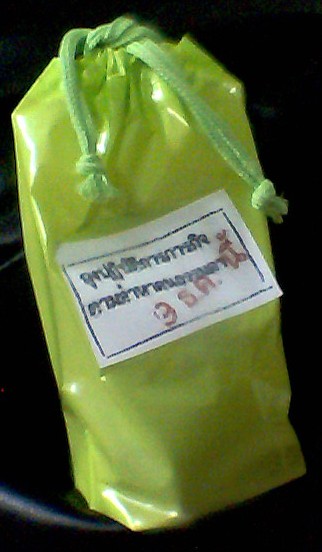
อลังการงานสร้างสรรค์ผ่านF0nt``
ชื่องาน:  ป้ายสติ๊กเกอร์แปะถุงใส่ของเชิญมาร่วมงานแฟร์
ณ วัน/เวลา:  ใช้อยู่ช่วงเดือนพฤศจิกา-ต้นเดือนธันวาคม 2549
F0nt ที่ใช้:  SP Unforgiven
เหตุผลประกอบ (ถ้ามี):  คนเลือกเขาบอกว่า "เออ อันนี้แหละ เจ๋งดี เท่ๆ ชอบๆ" ...ขนาดนั้นเลย (-*-)
ภาพประกอบ:
ป้ายเปลือยๆ
ป้ายบนถุง (ใช้มือถือถ่าย+มือสั่น ภาพก็เลยไม่ค่อยชัด ขอโทษด้วยค่ะ)